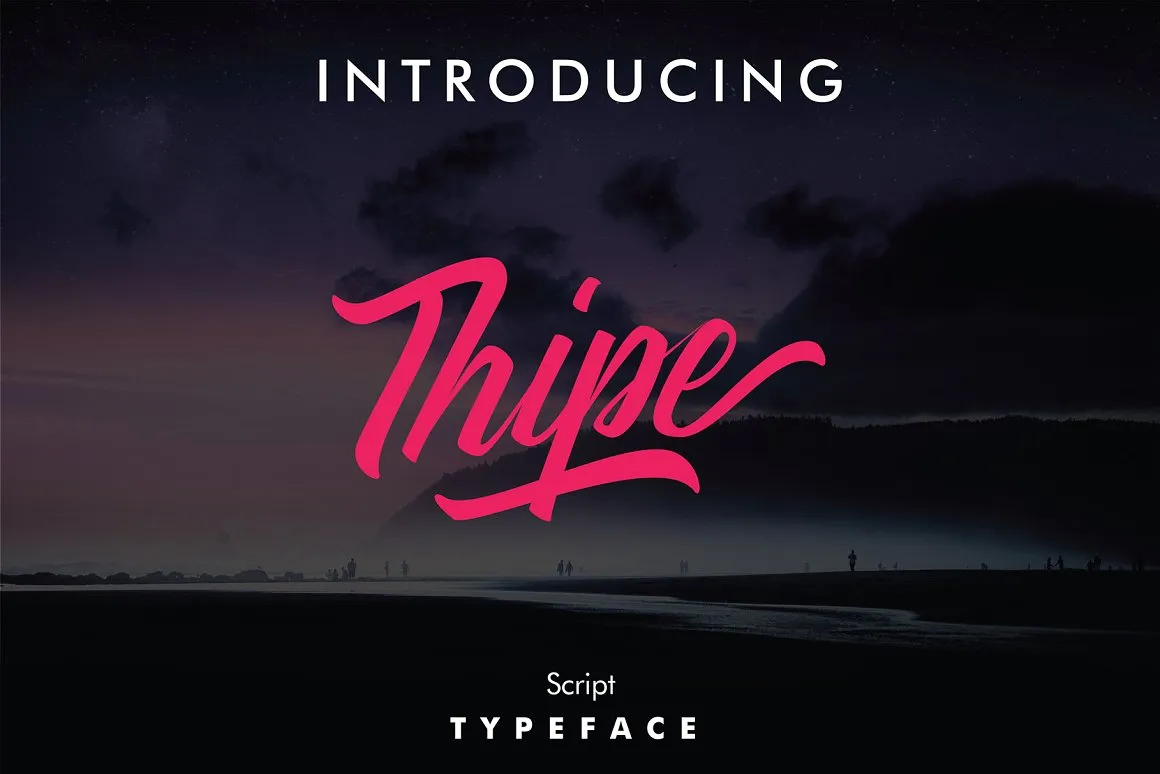
Thipe Script Font
A Thipe Script Font é uma nova fonte para escrita cáligráfica que traz um toque fresco e autêntico à sua paleta de tipos digitais. Desenvolvida por fathialghazi, essa elegante tipografia foi projetada em estilo de caligrafia manuscrita para atender uma variedade de necessidades gráficas. A Thipe Script é perfeita tanto para criar marcas de negócios como para produtos e embalagens, além de ser ideal para roupas e marcas de marca. Se você está procurando por uma fonte que seja capaz de trazer a personalidade do seu design à vida com estilo autêntico e sutileza elegante, a Thipe Script é a escolha certa. Esta fonte oferece mais caracteres para explorar o máximo da sua criação.